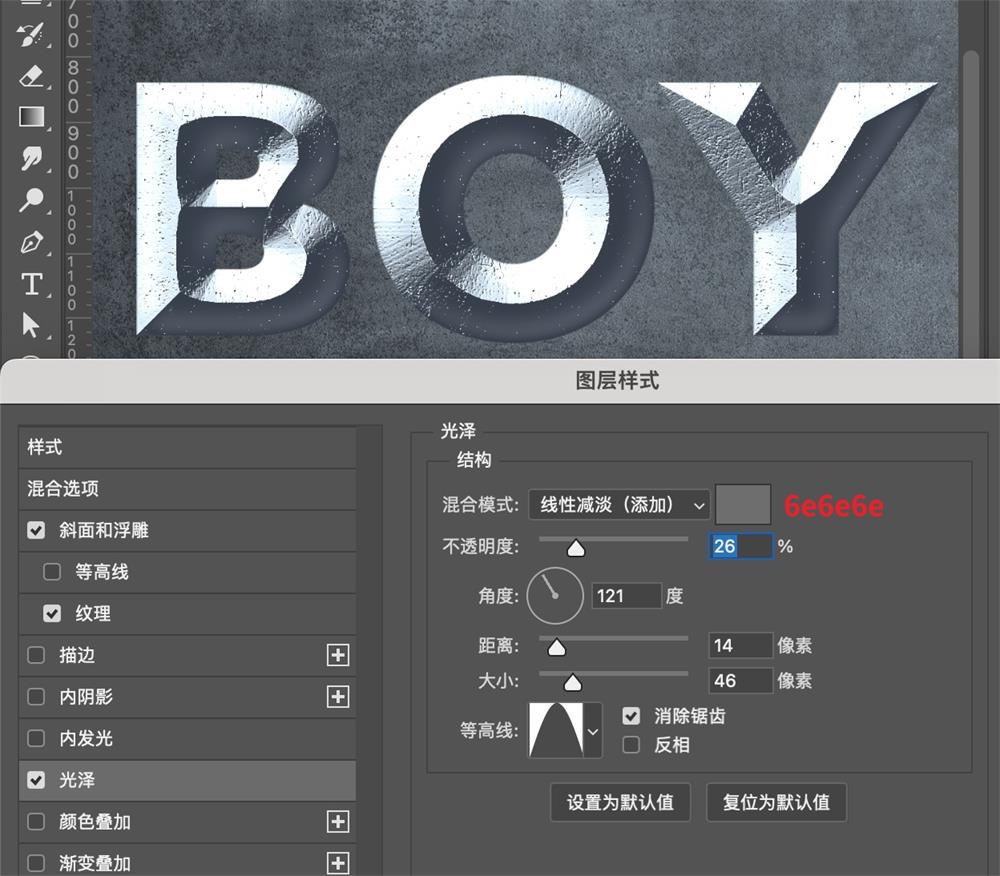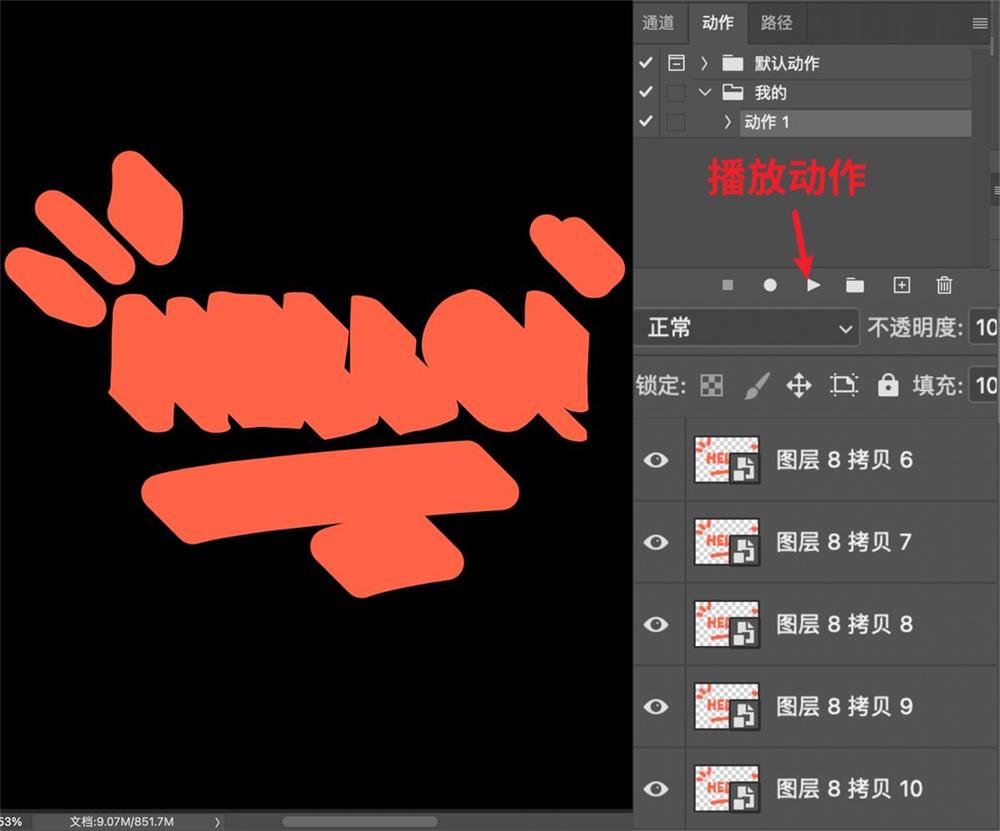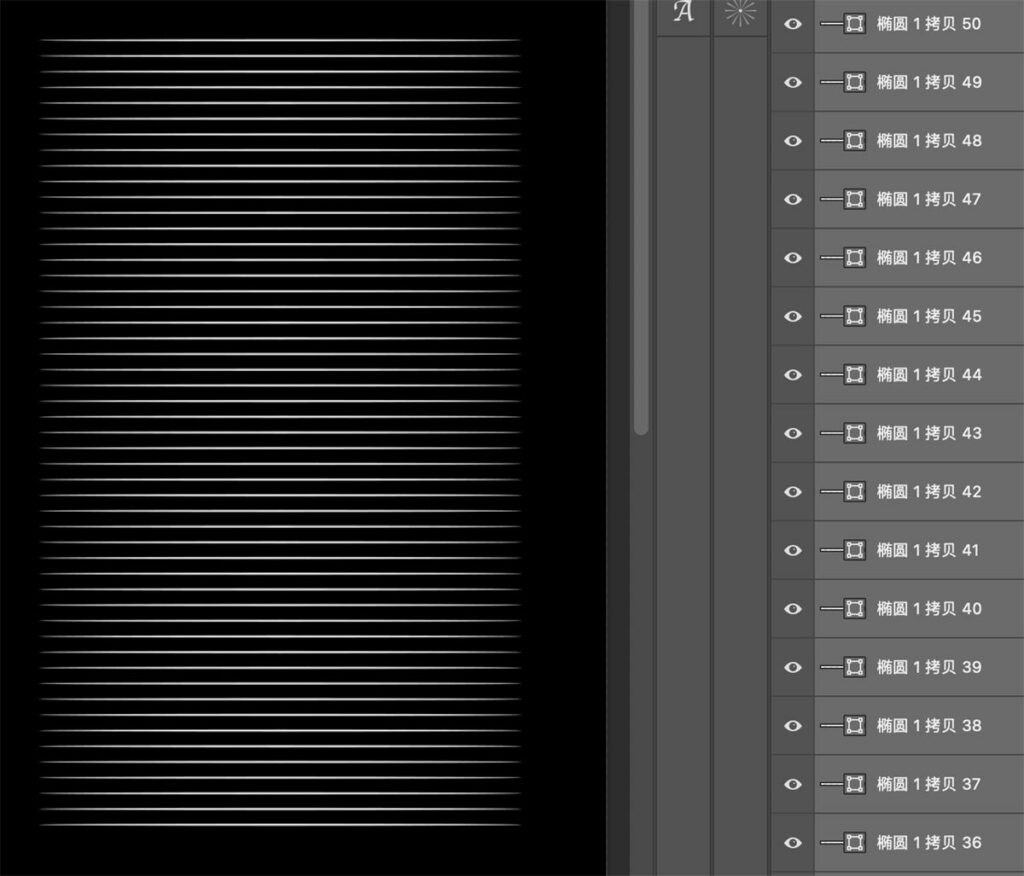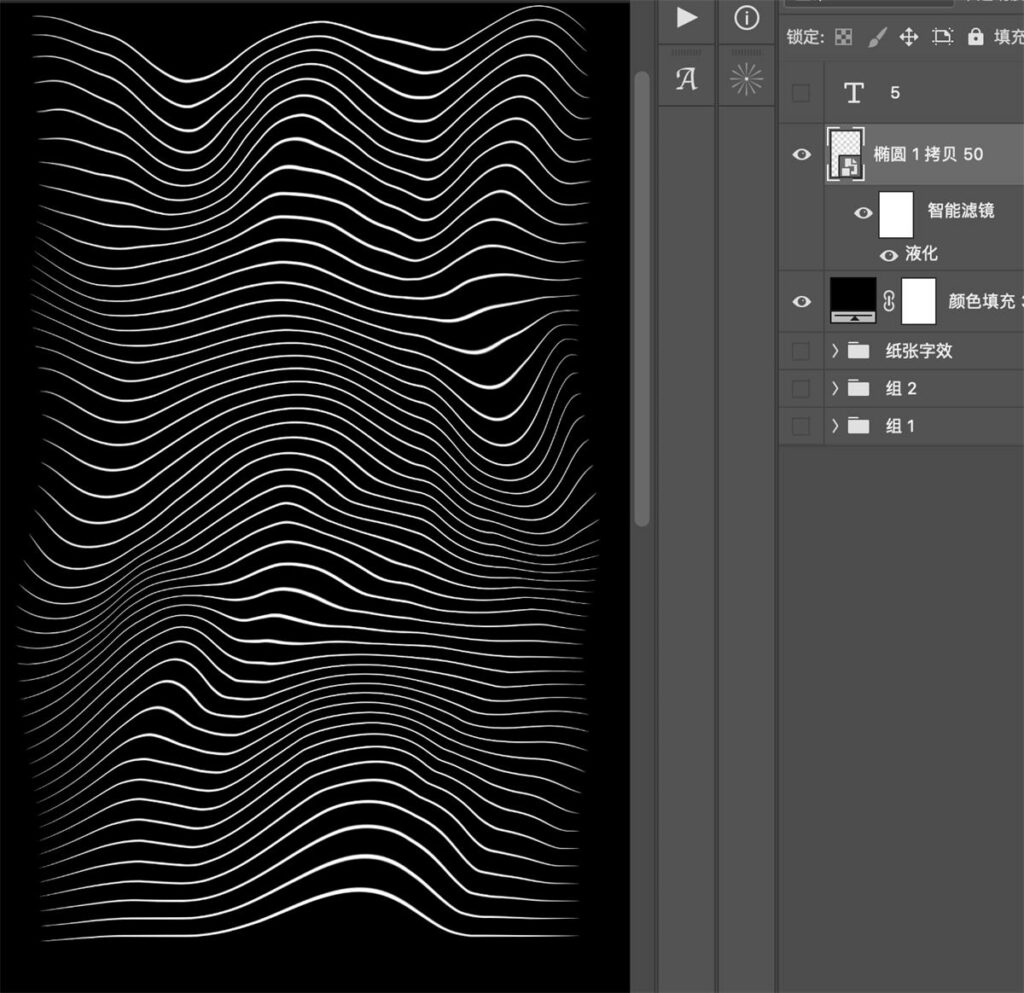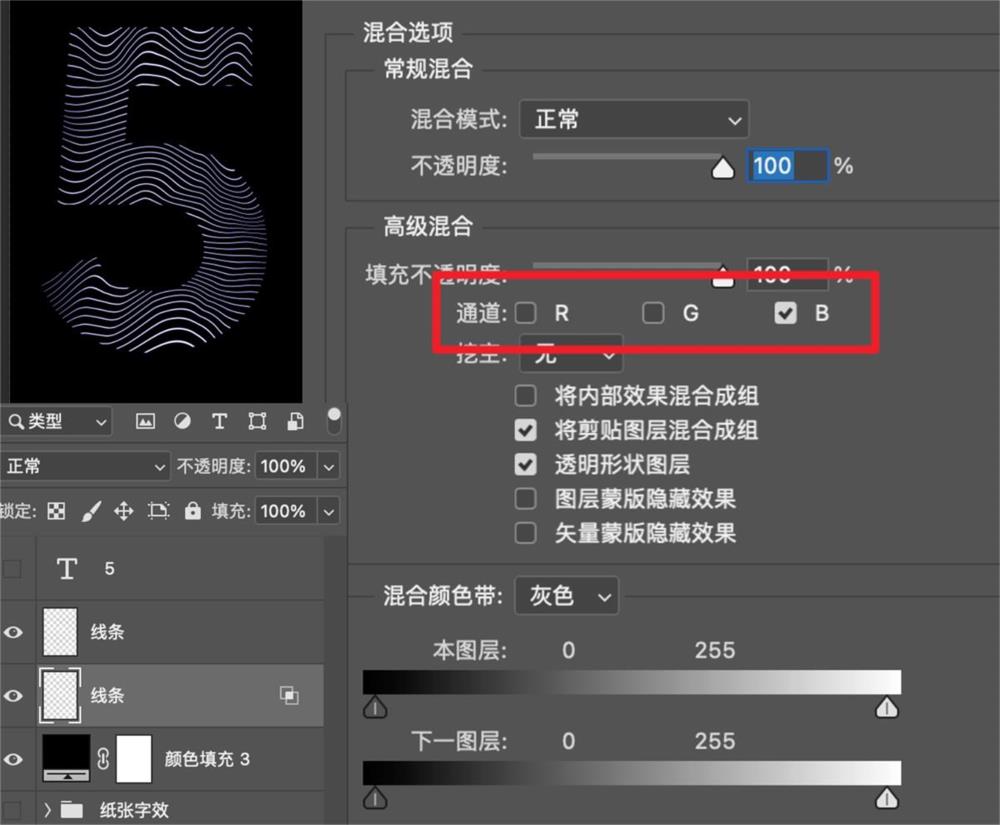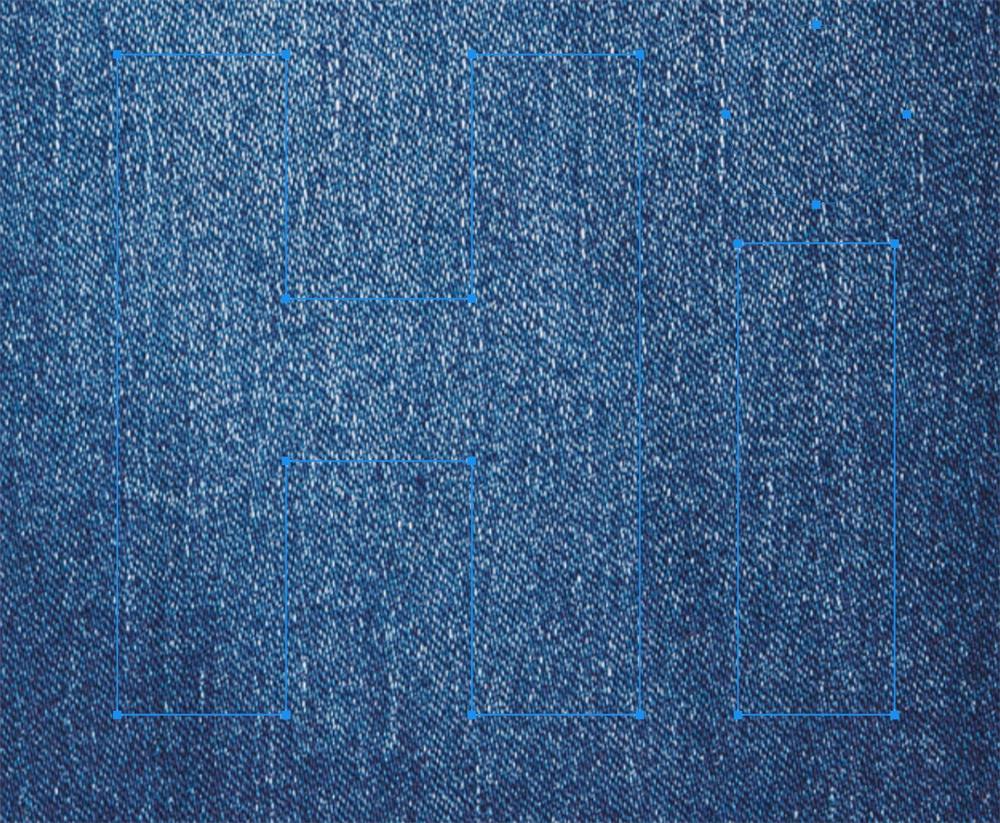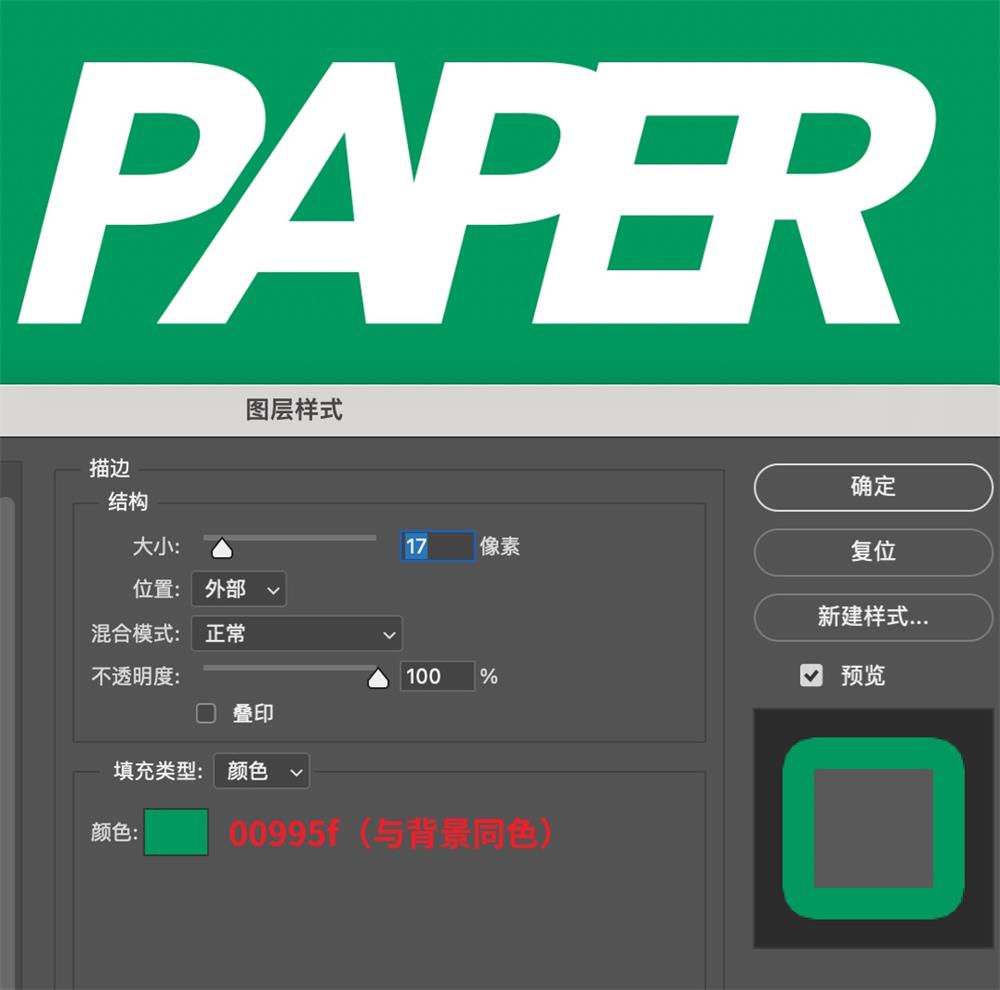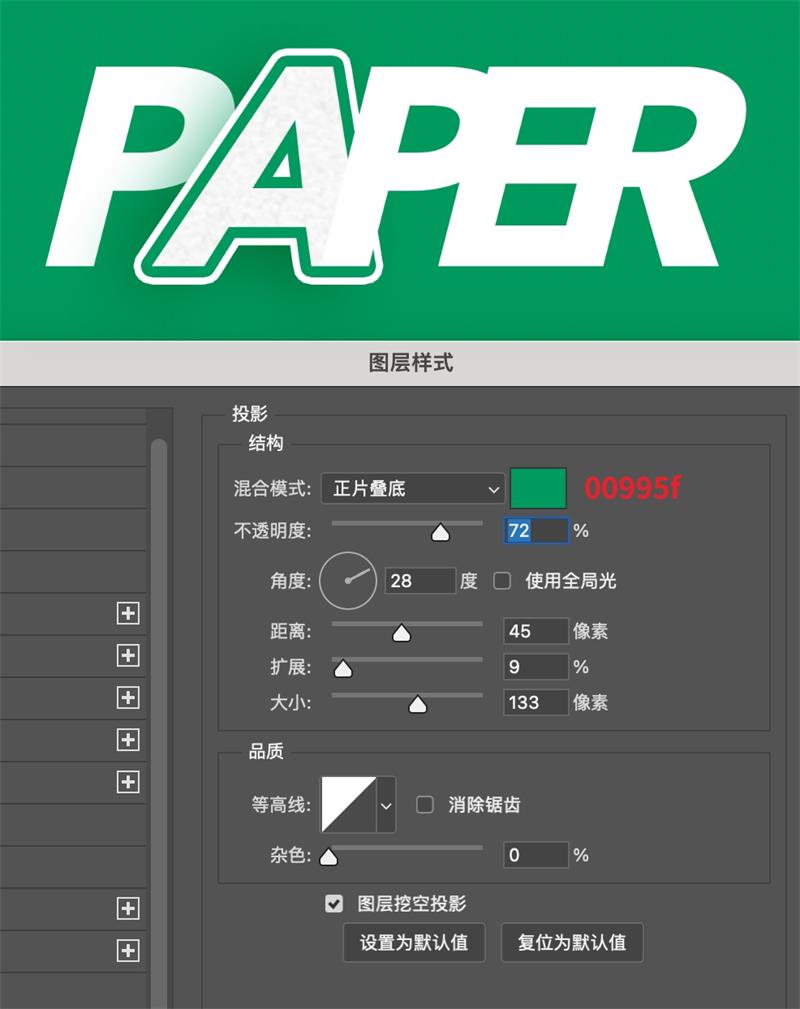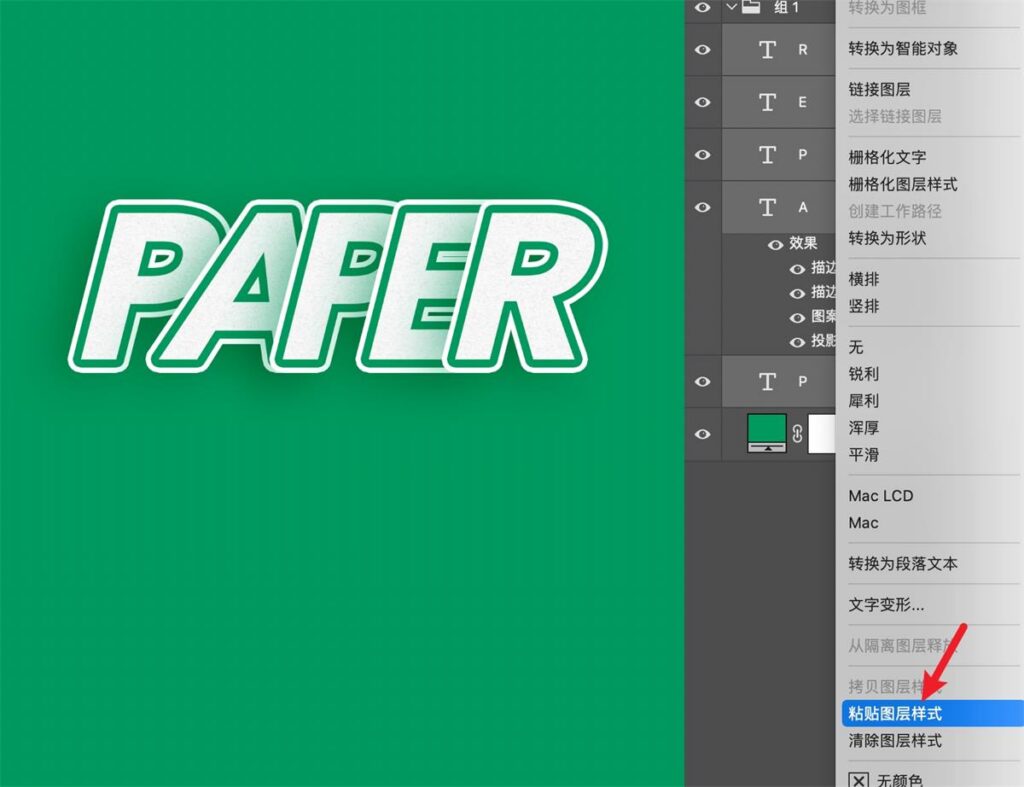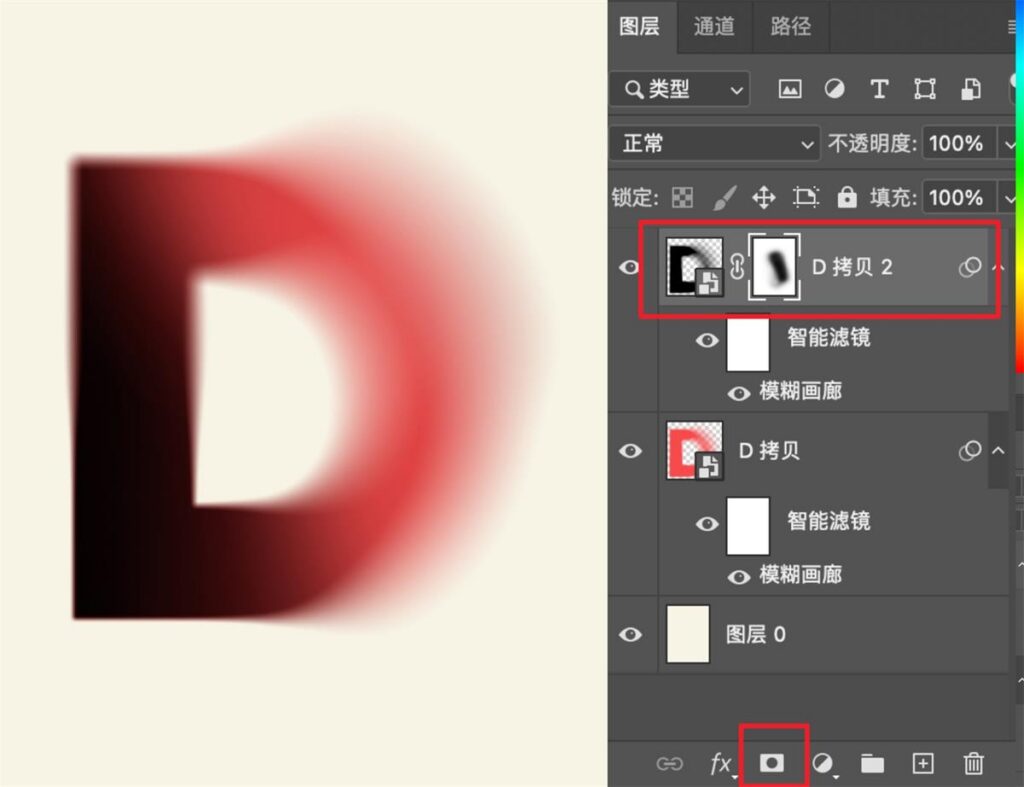
快速出效果!8个简单易上手的PS字效教程
字体特效是海报设计、主图排版、视觉封面创作的核心元素,好看的艺术字效可以瞬间提升画面质感、强化视觉层次,让普通排版升级为高级设计作品。很多新手设计师想要做出立体、金属、毛绒、弥散、条纹扭曲等创意字体,却苦于不懂参数调试、操作繁琐、成品效果生硬不自然。本文整理8种零基础可直接照搬的PS爆款字效实操教程,包含材质金属字、立体金属字、纸张字、彩虹立体字、条纹扭曲字、毛绒字、纸张描边字、渐变弥散字,步骤清晰、参数通用、上手即会;同时新增StartAI GPT生图一键生成艺术字体高效方案,解决手动做字耗时长、效果差、改稿麻烦的痛点,新手既能学习传统PS手工技法,也能借助AI快速出商用级字效海报,适配日常设计、电商排版、创意海报全场景使用。
前言
优质的字体特效,是设计作品的点睛之笔。不用复杂技法、不用高阶审美,掌握简单的PS图层样式、滤镜、重复变换技巧,就能轻松做出8种全网热门的高级艺术字效,快速完成整套字效海报制作。对于高频出图、快速改稿的设计场景,也可以借助StartAI GPT生图功能一键生成各类创意字体,兼顾学习进阶与高效出图。
一、8种零基础PS爆款字效手工教程
01. 材质立体金属字效
利用材质球+混合器画笔制作肌理金属字,质感随机自然、肌理丰富,适合潮流海报、科技风标题设计。
网上下载高清材质球素材,导入PS画布中备用;
使用圆形选框工具框选完整材质区域,按下Ctrl+J复制独立材质图层,Ctrl+D取消选区,隐藏原始素材图层;
在左侧工具栏切换为【混合器画笔工具】,选用PS自带第一款硬边圆笔刷,调整笔刷大小与材质球尺寸匹配;
选中材质球图层,按住Alt键点击材质区域吸取样式,将属性栏四项参数全部设置为100%;
直接使用画笔在画布上书写所需文字,自动生成自带材质肌理的字体;
若字体画面偏灰、对比度不足,按下Ctrl+L调出色阶面板,拉动滑块强化明暗对比,优化金属质感;
可替换不同金属、磨砂、纹理材质球,快速制作多款差异化材质金属字。
02. 精致立体金属字效
通过图层样式+路径模糊制作带长投影的高级金属立体字,光影层次饱满,适配商业海报、活动主标题。
新建1500×2100像素画布,导入适配风格的背景素材,输入主题文字,字体色值设置为#616970,右键文字图层选择【转换为智能对象】;
双击文字图层,打开图层样式,添加【斜面和浮雕】,调整参数打造立体金属厚度;
叠加【纹理】样式,模拟金属表面细微磨损肌理,提升真实质感;
添加【光泽】图层样式,调试参数优化金属暗部反光过渡,让光影更细腻自然;
Ctrl+J复制文字图层,右键清除复制图层的图层样式,将图层混合模式改为【正片叠底】;执行【滤镜-模糊画廊-路径模糊】,绘制右下方向路径,模式选择后帘同步闪光,制作自然长投影;
Ctrl+J再次复制投影图层,加深投影层次感,让画面更稳重;
背景图层上方新建图层,混合模式改为叠加、不透明度35%,使用黑白渐变工具拉出渐变,丰富背景明暗层次;
字体上方新建图层,右键创建剪贴蒙版,调整图层模式与不透明度,用柔边黑色画笔涂抹字体右下角,强化字体明暗过渡;
如需改字,双击智能对象缩略图,修改文字内容后Ctrl+S保存,原画布字体即可自动同步更新。
03. 复古纸张立体字效
结合透视变换+多层复制制作堆叠纸张字,复古文艺质感拉满,适合文艺海报、手账排版、古风设计。
输入文字,字体色值设置为#ECECEC,右键文字图层【转换为形状】;
Ctrl+T自由变换,右键选择【透视】,拖动控制点调整出自然透视效果;
双击图层添加双重内阴影:第一层混合模式正常、颜色#FFFFFF;第二层混合模式正片叠底、颜色#000000,按参考参数微调细节;
Ctrl+J复制文字图层,Ctrl+T自由变换,轻微拉高文字并微调透视,回车确认;
连续按下5次Ctrl+Alt+Shift+T,重复变换复制操作,生成多层堆叠字体效果;
全选所有文字图层,执行【图层-排列-反向】,规整图层顺序,复古纸张堆叠字效完成。
04. 多彩彩虹立体字效
利用PS动作批量复制图层,搭配多色叠加制作渐变彩虹立体字,色彩丰富、氛围感十足,适合潮流创意海报、节日视觉设计。
输入主题文字,可新建图层搭配画笔绘制简约装饰元素,丰富画面;
全选文字与装饰图层,右键【转换为智能对象】,执行【窗口-动作】打开动作面板;
新建录制动作,Ctrl+J复制图层,Ctrl+[下移图层,按方向键↓、→轻微移动图层位置,完成后停止动作录制;
持续点击播放动作,批量生成多层文字图层,形成自然立体厚度;
最顶层文字图层添加【颜色叠加】,填充白色#FFFFFF,作为字体顶面;
将剩余图层每5-10层分为一组,共5-7组,每组叠加不同彩虹色系颜色;
全选所有字体图层编组,新建图层创建剪贴蒙版,调低不透明度,用柔边黑画笔涂抹暗部,强化立体光影,彩虹字效制作完成。
05. 条纹扭曲字效
结合重复变换+液化滤镜制作动感条纹扭曲字体,潮流动感、视觉冲击力强,适合潮流海报、音乐节、潮流服饰排版。
选用椭圆工具,绘制一个扁平细长的椭圆线条;
Ctrl+T自由变换,按住Shift+↓垂直下移线条,回车确认,连续按下Ctrl+Alt+Shift+T重复变换,生成整齐排列的条纹组;
全选条纹图层Ctrl+E合并,右键【转换为智能对象】,执行【滤镜-液化】,用画笔涂抹条纹,打造自然扭曲动感效果;
输入文字、调整大小后隐藏,按住Ctrl点击文字缩略图载入选区,选中条纹图层添加图层蒙版,生成条纹字体轮廓;
栅格化图层并应用蒙版,Ctrl+J复制条纹图层;选中下层图层,取消R、G通道,保留蓝色通道;
使用大尺寸柔边涂抹工具局部涂抹字体,制作错位偏移特效,动感条纹扭曲字完成。
06. 质感毛绒字效
自定义毛绒笔刷+路径描边制作立体毛绒字体,肌理柔软真实,适合可爱风、童趣、潮流治愈系海报设计。
使用钢笔工具绘制流畅曲线路径,调小画笔尺寸备用;